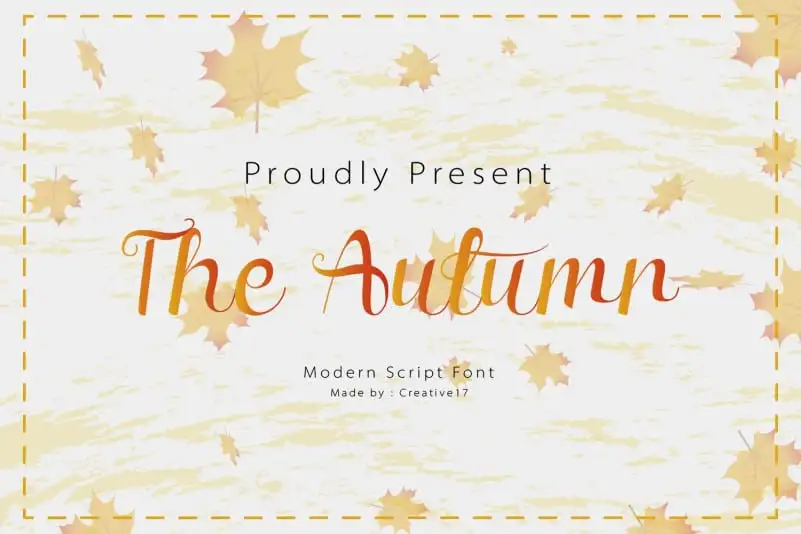
The Autumn Calligraphy Font
A fonte “The Autumn Calligraphy Font” oferece uma experiência única para quem busca expressar elegância e delicadeza nas criações digitais. Desenvolvida pelo designer Irfan Hidayat, essa fonte é inspirada na beleza das folhas de outono: uma delicadeza e fluidez em cada letra que transmitem um ar poético e sofisticado. Perfeita para designers querendo dar um toque especial a suas criações digitais, seja ela para invitações, cartões de visita ou bandeiras. Além disso, esta font é versátil o suficiente para se adaptar a uma ampla gama de projetos gráficos. Adquira “The Autumn Calligraphy Font” e deixe sua arte resplandecer com um charme único que representa a delicadeza das folhas em outono.